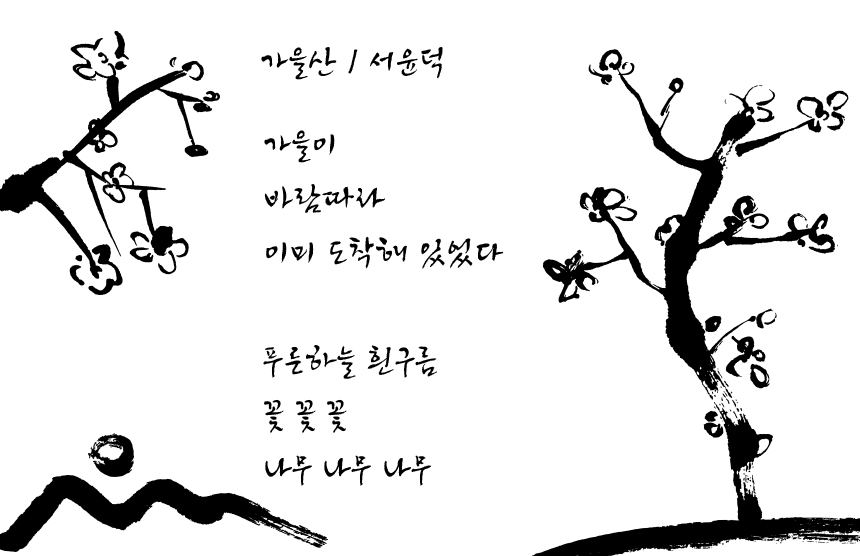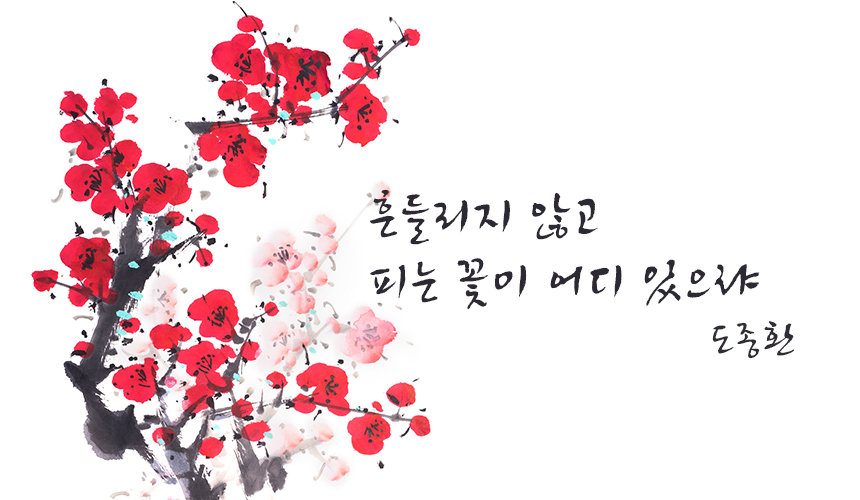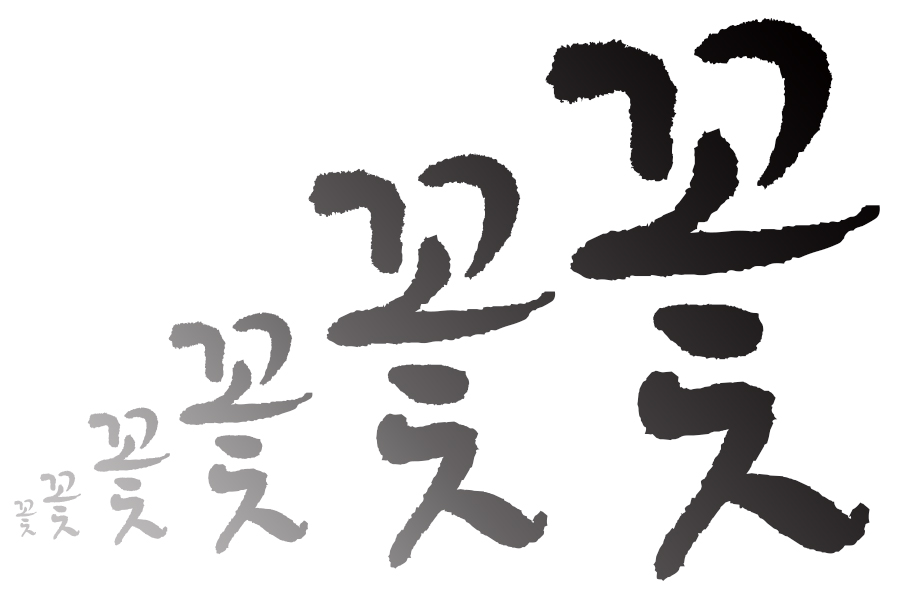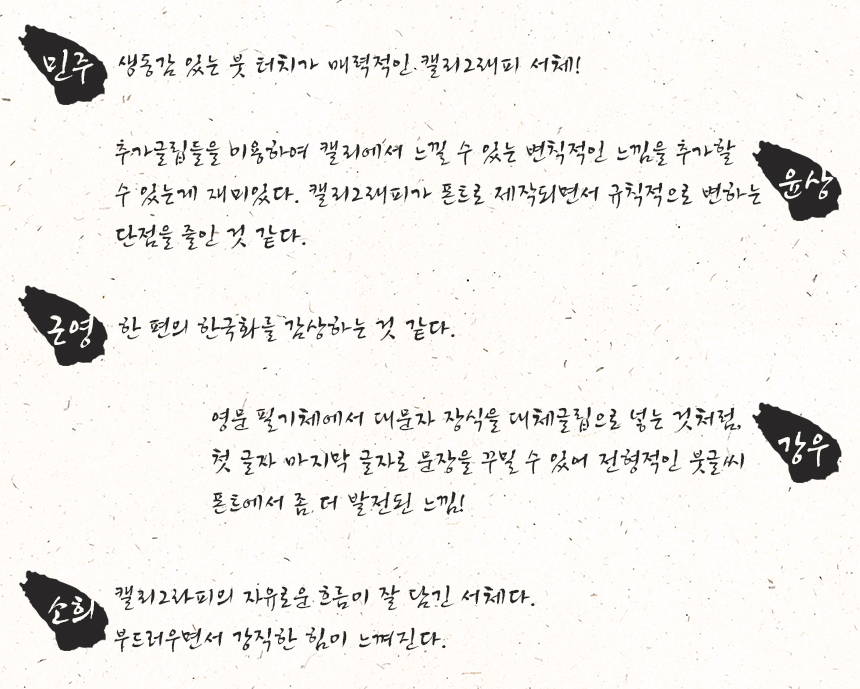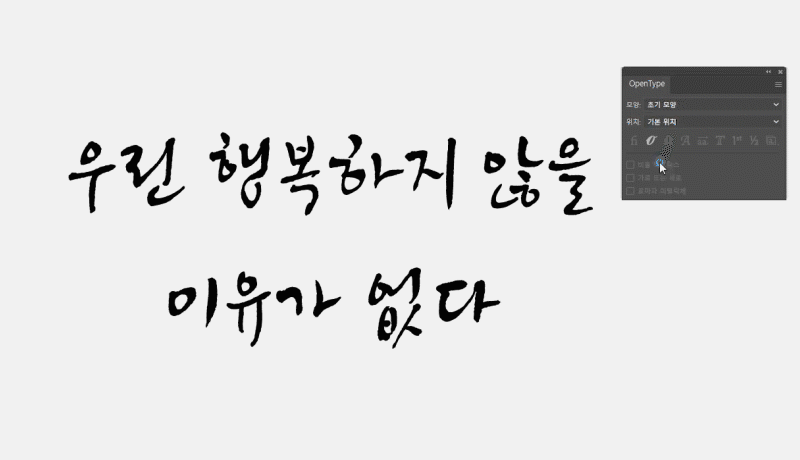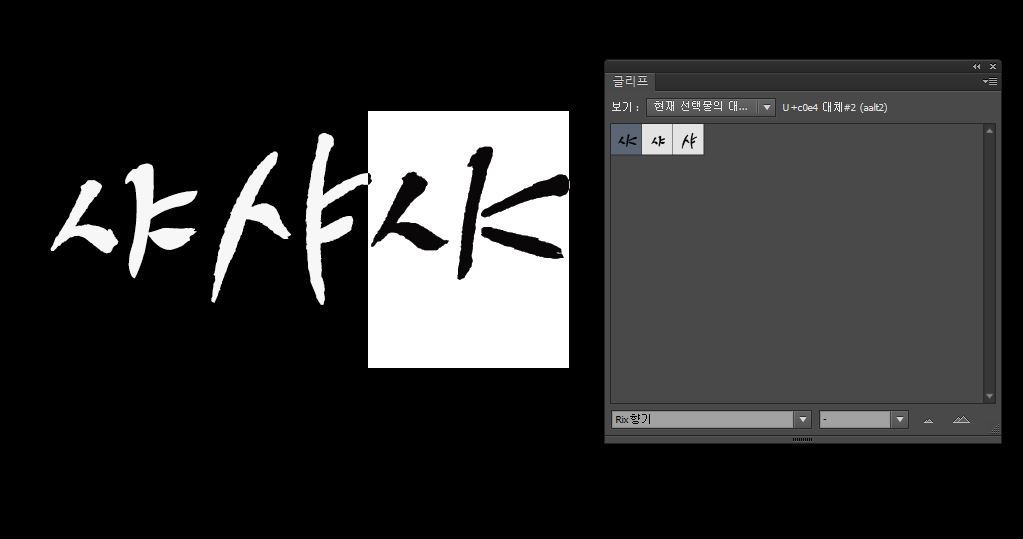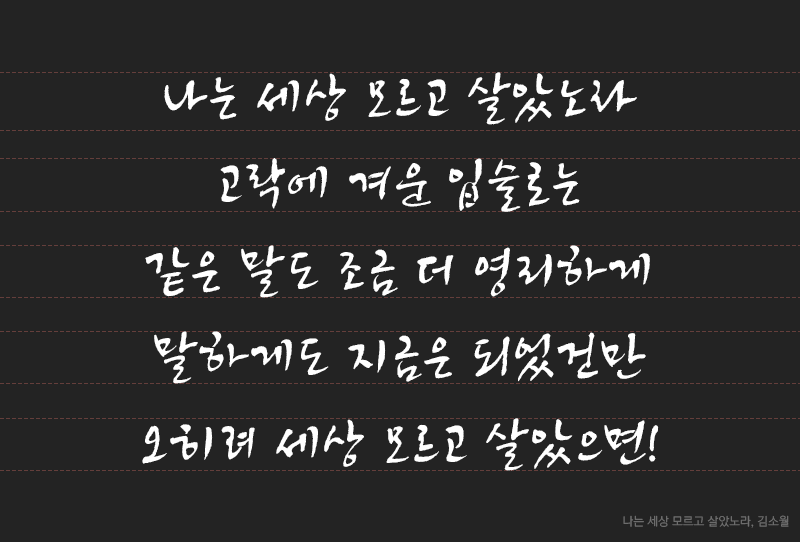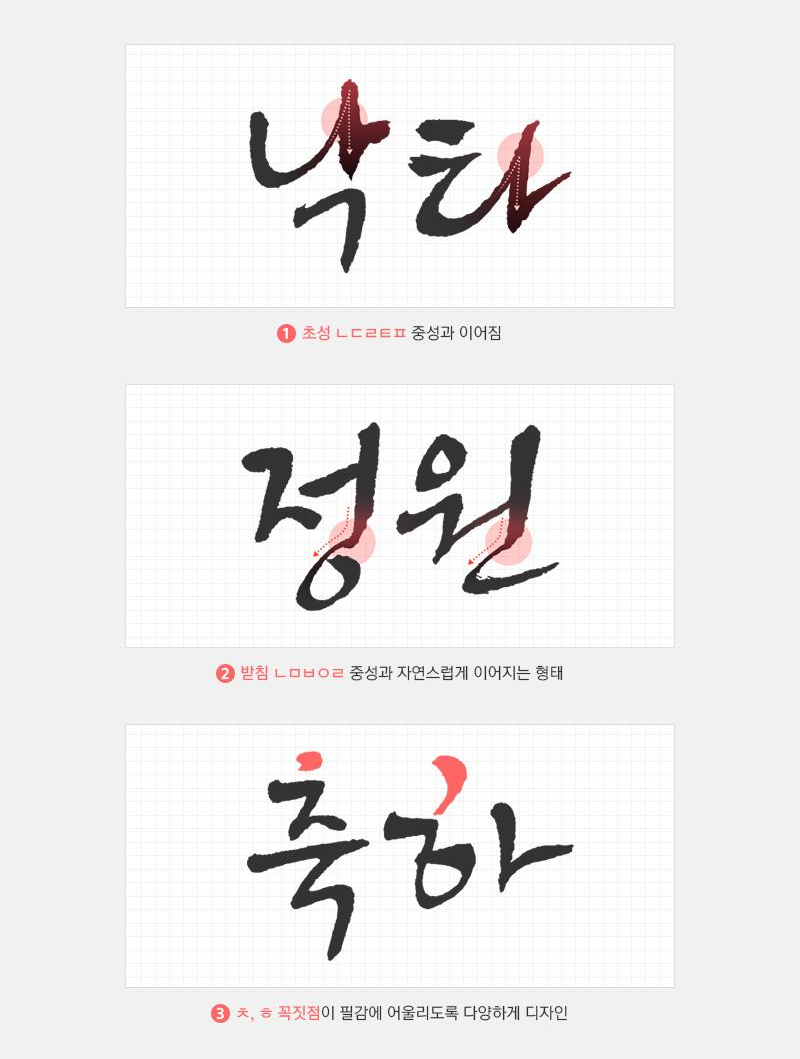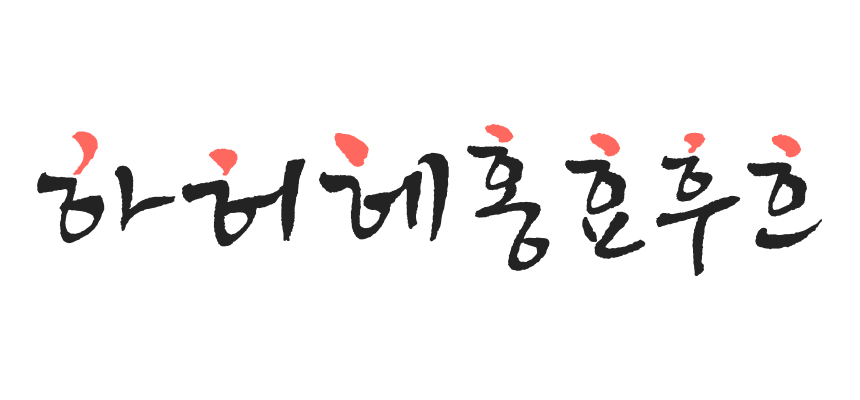
드디어 9월의 신서체가 출시되었습니다! 이번 서체는 매마른 감성을 촉촉히 적셔줄 유려한 매력의 캘리 폰트 「Rix향기」입니다. 이 폰트의 가장 특별한 점이라면 바로 캘리그라피 폰트라는 것인데요. 일러스트 파일로만 다운로드할 수 있었던 캘리그라피를 편리하게 사용할 수 있는 폰트로 만나보게 되었습니다. 그 과정의 중심에 있었던 김수정 디자이너와의 인터뷰 함께 보시죠:)
폰트를 알려면 디자이너를 알아야지_폰트 디자이너 인터뷰
안녕하세요, 수정 디자이너님. 8월에 이어 9월에도 만나게 되었네요(웃음) 이번에 나온 신서체는 이전 폰트와는 완전히 다른 스타일 같은데, 어떻게 제작하게 된 폰트인가요?
9월도 만나서 반갑습니다. 이번에 만든 폰트는 캘리그래피 폰트입니다. 기존에 회사에서는 이 캘리그래피 글자를 ai 형식으로 판매했었습니다. ai 자소 글자를 디자이너가 필요한 단어를 직접 제작하여 쓰는 형식이었습니다. 일일이 조합해서 쓰는 것이 캘리그래피 특유의 느낌을 더욱 살릴 수 있어 좋은 방법이라고 생각하지만, 긴 문장을 쓸 때 다소 긴 시간이 소요되는 부분을 개선하기 위해 캘리그래피 자소 글자를 폰트화하는 작업을 하게 되었습니다.
비전문가인 제가 봤을 때 폰트가 '붓글씨 같다'는 느낌이 많이 들어요. 다른 폰트들을 디자인할 때와 다른 점이 있었다면?
좋았던 점은 글자가 멋있고 획의 필감이 너무 좋아서 한 글자, 한 글자 자체의 완성도가 높았습니다. 그런데 하나하나 너무 예쁜 글자가 문장에서 쓰이는 위치에 따라 어색해 보이는 문제가 있었습니다. 적절한 기준을 찾아서 문장을 조화롭게 쓸 수 있도록 폰트화하는 것이 어려웠습니다.
아무래도 처음 시도하는 스타일이라 어려웠겠어요. 독특한 캘리그라피 서체 Rix향기, 어떻게 쓰였으면 좋겠나요?
캘리그래피 특유의 율동감이 시의 운율에 잘 어울린다고 생각해서 시집에 쓰이면 좋을 거 같다고 생각하면서 제작하였습니다. 완성된 폰트를 이미지에 적용해 보는 과정에서 과일, 채소, 꽃 등 자연적인 이미지 패키지에도 잘 어울린다고 생각합니다.
보통 폰트를 디자인할 때 가장 중요하게 생각하는 부분은 무엇인가요?
문장을 길게 썼을 때 자연스러워 보이도록 하는 것과 기존 캘리 느낌을 최대한 살리는 부분을 중요하게 생각하였습니다. 자유롭게 쓰인 글자를 폰트로 만드는 것은 기존에 폰트를 만드는 것과는 다른 접근이 필요했습니다. 캘리그래피 특유의 느낌을 살리기 위해 어두, 어미를 대체글립을 사용하여 문장에서 자연스러운 느낌을 살리려고 했습니다.
캘리그라피를 쓰다, 글자를 그리다.
서체를 보는 순간 동그란 꽃잎과 단단한 줄기를 가진 매화나무가 떠올랐습니다. 이른 봄 추위를 무릅쓰고 가장 먼저 꽃을 피워내는 매화는 선비의 지조와 절개를 상징하는 사군자 중 하나이기도 하죠. 아름다운 선과 강직한 힘을 함께 가진 「Rix향기」는 고귀한 자태와 은은한 향기를 품은 매화꽃을 닮았다는 생각이 들었습니다.
볼수록 매력 있고 쓸수록 새로운, 자꾸만 쓰고 싶어지는 폰트. 먹을 담뿍 머금은 붓으로 쓴 글씨 같은데, 타이핑을 하면서 하얀 모니터 화면으로 나타나는 모습을 보고 있으면 더욱 새롭습니다. 특히 폰트를 한 자 한 자 크-게 써보면 이 서체를 얼마나 섬세하게, 정밀하게 만들었는지 알 수 있습니다.
글을 썼다기보다는 그렸다는 표현이 더 어울릴까요? 붓으로 그려낸 듯한 글자 하나하나가 자세히 들여다볼수록 마치 그림 같습니다. 어떤 글자를 쓰느냐에 따라 부드럽게, 때론 힘 있게 느껴집니다.
한 편의 그림같은 서체
동양화, 한국화의 감성이 물씬 풍기는 「Rix향기」는 아무래도 서체를 처음부터 기획하고 제작하는 폰트디자이너에게도 약간은 생소하고 새로운 스타일의 폰트였을 것 같은데요. 그래서 직접 여쭤봤습니다.
폰트디자이너들이 실제로 써본 'Rix향기'는 어땠나요?
역시나 함께 폰트를 디자인하는 입장에서 바라본 폰트에 대한 평을 듣고 보니 생각지 못했던 부분들도 알게 되고, 폰트의 느낌이 확 와닿는 기분이 들었어요. 고민하고 노력한 시간을 알기에 그만큼 더 애정을 갖고 자세히 봐주신 것 같습니다. 디자이너분들의 센스와 디테일을 옅볼 수 있었던 감상평에 감사하다는 말씀 전하면서, 좀 더 깊이 있게 「Rix향기」 폰트에 대해 알아볼게요.
다양한 표현을 위한 '대체글립'
이번 폰트에서는 새로운 기능이 추가되었는데요. 이 '대체글립'을 사용하면 더욱 다양한 표현이 가능해집니다. 대체글립(동어반복글립)은 Adobe 계열의 프로그램에서만 사용 가능하며, '문맥 대체(Contextual alternates)' 혹은 'OpenType' 기능을 활성화해야 합니다.
같은 글도 대체글립을 사용하여 다른 느낌을 줄 수 있고, 필감을 더욱 살릴 수 있습니다. 시에서 자연스러운 운율감이 느껴지지 않나요?「Rix향기」서체는 대체글립이 가능한 어두 132자, 어미 74자 총 206자를 지원합니다. 캘리그라피로만 가능했던 부분을 일부 폰트로 실현해 사용자가 더 다양한 표현을 할 수 있도록 했어요!
다채로운 즐거움, Rix향기
기본적인 특징은 먹의 뭉침과 번짐, 획 굵기의 변화가 다채롭기 때문에 빠르게 뻗어 내려간 필감이 살아있다는 것.
'ㅎ'으로 여러 글자를 써봤습니다. 꼭짓점이 이렇게 다 다를 수 있나요?
어떤 조합이냐에 따라 변화되는 게 재밌다보니 다른 글씨들도 자꾸 써보게 되네요. 이렇게 여러가지 형태가 폰트로 구현된다니 정말 새롭고 신선한 느낌이 듭니다.
| Rix향기 적용 이미지 샘플
제품 패키지나 카드, 배너 포스터, 택 디자인 등에 사용해본 샘플입니다. 아무래도 한국적인 분위기가 나는 붓글씨 서체라 그런지 민족 고유의 명절 추석의 이미지와 자연스럽게 잘 어우러집니다. 또한 세련되고 고급스러운 패키지에도 잘 어울리죠. 컬러나 일러스트와의 조합에 따라 다양한 디자인에 적용할 수 있어요.
내 맘대로 조합하는 캘리그라피
이번 폰트는 특별히 캘리그라피 파일로도 가능합니다. 그동안 캘리그라피를 폰트로, 폰트를 캘리그라피로도 쓸 수는 없는지에 대한 문의가 종종 있었는데요, 「Rix향기」는 폰트로도 캘리로도 쓸 수 있도록 활용성을 업그레이드했답니다.